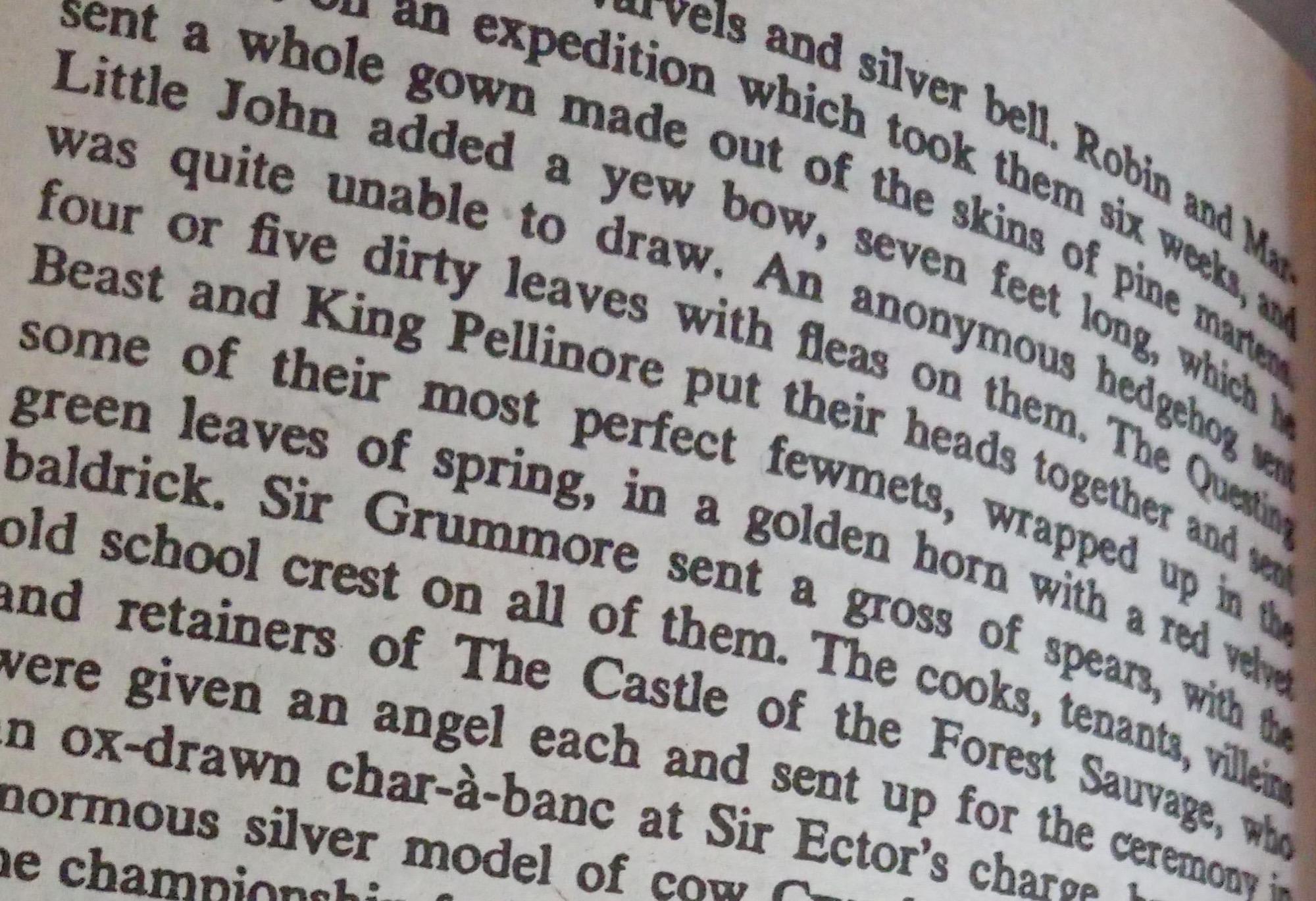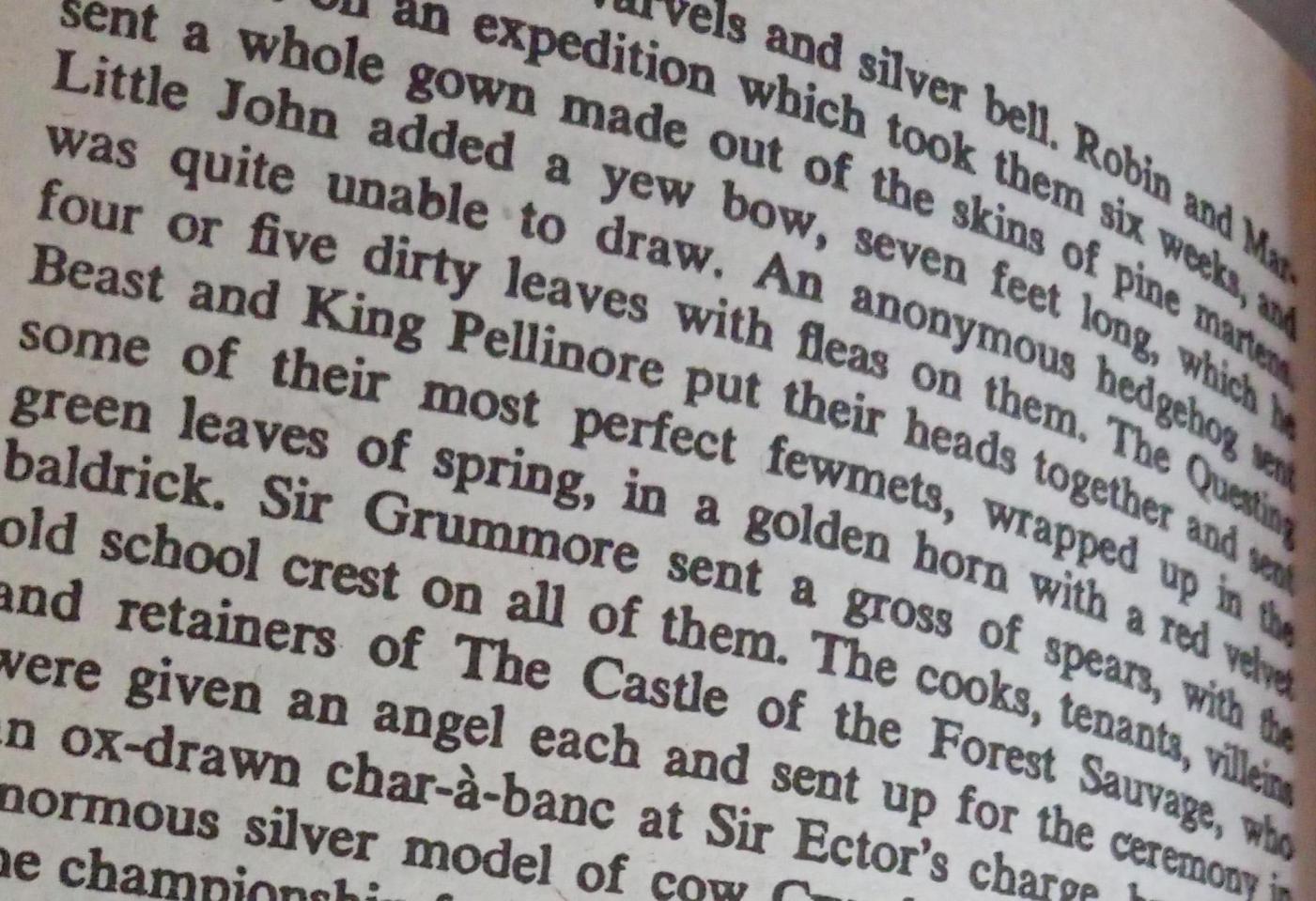
Buchdruck: US-Taschenbücher 70er / 80er / 90er Jahre - Frage zur Schriftdicke
Ich habe eine Frage zum Druck von Taschenbüchern, genauer gesagt von welchen, die vor allem in den 1970-1990ern in den USA erschienen sind. Diese waren oft recht klein gedruckt, waren jedoch trotzdem gut zu lesen, weil die Schrift recht dick ist.
Meine Frage nun: Weiß jemand, ob dafür einfach ein dicker oder semi-dicker Schnitt genutzt wurde oder ob die Schrift einfach aufgrund des Druckverfahrens so dick aussah? Heutige Taschenbücher sehen nicht mehr so aus.
Ich habe einmal exemplarisch ein Foto eines Buches angehängt, das ich im Netz gefunden habe. Meine ganzen Taschenbücher, die so gedruckt sind, liegen leider nur schwer zugänglich im Keller :-)
in dem Beispiel das ist die Times (Regular), die sieht normalerweise nicht so schwarz aus. Da ich meine hier einen Offsetdruck zu sehen und man mit physischer Überdosierung der Farbhaltung niemals ein solches Druckergebnis erzielen könnte, ohne daß sich die Farbe auf dem nächsten Bogen ablegt, kann ich mir eigentlich nur eine absichtliche (?) Überbelichtung beim Herstellen der Platten vorstellen, um die Schrift aufzubacken.
Ja, ich bin auch ein wenig ratlos, wieso die Schrift so dick ist, allerdings habe ich von Buchdruck auch gar keine Ahnung, vor allem nicht, wie das in den z.B. 80er Jahren gemacht wurde.
Pauschal kann man das schwer beantworten. Da kommen neben der Schriftart viele Dinge zusammen. Die verschiedenen Druckverfahren: Bleisatz, Fotosatz, Digitalsatz. Die verschiedenen Verfahren und Schritte der Herstellung der Druckplatte für die letzten beiden letztgenannten Kategorien. Die Einstellungen von Farbe und Maschine beim tatsächlichen Druck. Die Art und Saugfähigkeit des Papiers …
Wie schon gesagt ist aber eher nicht zu erwarten, dass das Druckbild in dem Bildschirmfoto die Originalschrift gut wiedergibt.
Wie Bleisatz (und Buchdruck) sieht das aber eher nicht aus. Die Buchstabenabstände sind viel zu eng und werden ja stellenweise zu "Ligaturen". Ich vermute - wie der Kollege Stötzner - eher etwas verunglückten (ob nun mit ohne ohne Absicht) Licht- bzw. Fotosatz, was auch die ungewöhnliche Fette erklären würde und anschließend Druck im Offset. Zumal viele Taschenbücher ja auch im Rollenoffset gedruckt wurden ...
Mit Buchdruck hat das höchstwahrscheinlich nichts zu tun.
Ich habe sowas gesehen als ich vor einigen Jahren nach einer schönen Ausgabe des Herrn der Ringe für meinen Jungen suchte. Da gab es allerlei Kostbarkeiten was den Einband anging: Leder, Goldschnitt, alles vom Feinsten. Sobald man die Bücher aber aufschlug war der Zauber vorbei: billiges Papier und der schmierigste, schmuddeligste Druck, den man sich vorstellen kann. Gesetzt wurde da sicher nichts, sondern einfach eine ältere Ausgabe abfotografiert.
Im Ernst – das gibt’s? Einfach nur abfotografiert? :shock: Man sollte wirklich nicht denken, dass einen nix mehr überraschen kann … :neenee:
Gesetzt wurde da sicher nichts, sondern einfach eine ältere Ausgabe abfotografiert.
Beim Herrn der Ringe gab's ja auch einmal die Zeit, wo in den USA das Copyright auslief (oder das zumindest gedacht wurde), und die für den Herrn Tolkien grässliche Form des Taschenbuchs gewählt wurde. Ich glaube das war dann sogar eine Mischung aus eigenem Satz und Photo-Facsimile.
Wenn der neue Satz aufwändig wäre oder man ganz klar Kosten sparen will wurde/wird das doch m.W. nach häufig gemacht. Oder am besten beides, wie bei Musiknotenbüchern und Comics.
abfotografiert
Es gab bis in die 90er-Jahre in Asien eine Art »Industrie«, die sich darauf verlegt hatte, halblegale »Neuauflagen« älterer Lexika etc. zu veröffentlichen. Da wurde das genauso gemacht (mit einer Reprokamera, of course). Bei den wenigen seriösen Ausgaben wurden Korrekturen neu gesetzt und einmontiert. Das waren dann die einzigen scharfen Zeichen im ganzen Buch.
Der Terminus „abfotographieren“ ist m. E. hier nicht ganz angebracht.
Wie schon von Norbert erwähnt, handelte es sich um Reprokameras mit denen das bewerkstelligt wurde.
Diese Reprokameras, wenn sie von einem Fachmann bedient wurden, konnten eine Vorlage so wiedergeben (reproduzieren), dass der Unterschied zum Original praktisch nicht erkannt wurde.
Der heutige Scanner entspricht im wesentlichen der damaligen Reprokamera.
Dass auf dem Gebiet der Schriftreproduzierung viele Schriften zu fett oder zu mager im Druck waren, lag in erster Linie an der Vorlage.
Auch ich bewerte nicht, ich wollte nur den Hinweis geben, dass „Fotografie“ und „Reprofografie“ zwei verschiedene Fachbereiche sind. Deshalb waren dies auch zwei verschiedene Berufe.
Nachdem ich jahrelang mit Reprofotografen zusammengearbeitet habe, ist es für mich ein Unterschied ob von einem Foto oder von einem Repro die Rede ist..
Reproduktion ist immer eine Verschlechterung, in jedem Verfahren. Qualitätsverluste sind nicht zu vermeiden. Ich hab meine von mir vom Bleisatz gedruckten vier Bücher erst scannen lassen für einen Sammelband als Faksimile, und als da die ersten Muster vorlagen, haben wir in der Produktion noch für einen Haufen Geld das Pferd gewechselt und einen sehr guten Kunstfotografen gefunden, der im Studio Repros machte, weil in seinen Fotos die Atmosphäre der Buchseiten zumindest teilweise eingefangen werden konnte. Mit Scannen war da nichts zu machen, das war vom Original zu weit entfernt.